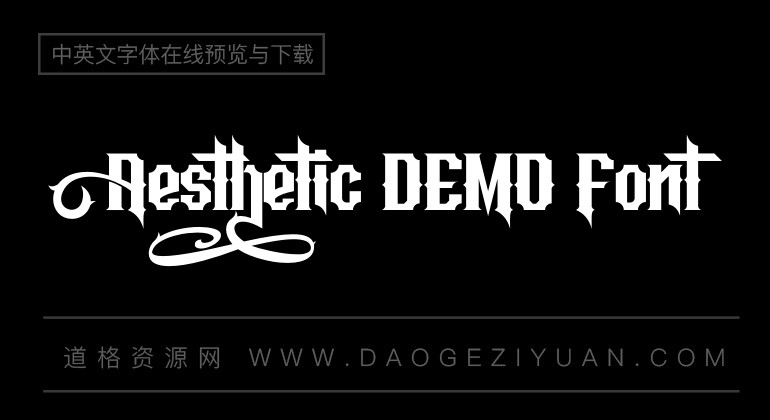
Aesthetic DEMO Font
Aesthetic DEMO Font是一种流行的装饰性字体,通常用于设计和艺术作品中,有时也会用于文本标题或标语中。这种字体包含各种华丽的装饰元素,如弯曲的线条、花纹、装饰符号和各种其他装饰。这些元素通常呈现出非常艺术化的外观,使得这种字体非常显眼和引人注目。 Aesthetic DEMO Font是一种非常多样化的字体,有许多变体和样式可供选择。有些版本会更注重装饰元素的数量和复杂性,而其他版本则更注重字母形状的优雅和流畅。这种字体可以用于很多不同类型的设计和艺术项目,使得它成为了许多设计师和艺术家的首选之一。
Aesthetic DEMO Font是一款非常不错的手写艺术字体,具有很好的视觉感,适合于文化类的宣传设计、商业类品牌的广告和产品包装设计以及个性化文字排版等较多场景。